21 Font Romawi Terbaik 2023 (Gratis & Premium)
Diterbitkan: 2023-08-03Apakah Anda seorang desainer grafis yang sedang mencari font yang sempurna untuk meningkatkan desain proyek Anda? Tidak perlu mencari lagi! Dalam postingan blog ini, kita akan menyelami dunia font Romawi dan menemukan 21 opsi terbaik untuk tahun 2023, baik gratis maupun premium.
Sekarang Anda mungkin bertanya-tanya, mengapa font Romawi? Nah, font Romawi dikenal karena keanggunan dan keserbagunaannya yang tak lekang oleh waktu.
Mereka dapat menambahkan sentuhan kecanggihan pada desain apa pun, menjadikannya pilihan tepat untuk proyek mulai dari logo dan branding hingga situs web dan materi cetak.
Pada artikel ini, kami akan menampilkan pilihan font Romawi pilihan yang pasti akan menginspirasi dan meningkatkan karya kreatif Anda.
Namun bukan itu saja – kami juga akan membagikan beberapa statistik dan fakta menarik tentang font ini, seperti popularitasnya di kalangan desainer dan keserbagunaannya di berbagai gaya desain.
Jadi, apakah Anda ingin menambahkan sentuhan klasik ke proyek berikutnya atau sekadar memperluas pustaka font, kami siap membantu Anda. Teruslah membaca untuk menemukan 21 font Romawi terbaik tahun 2023 dan bawa game desain Anda ke level selanjutnya.
Font Romawi Premium Terbaik
Selamat datang di dunia font Romawi, tempat keanggunan dan kecanggihan bertemu dalam harmoni yang sempurna.
Di bagian ini, kami akan menampilkan font Romawi premium terbaik yang dijamin akan meningkatkan proyek desain Anda ke tingkat yang baru. Pastikan untuk memeriksa font-font menakjubkan ini dan biarkan kreativitas Anda bersinar!
Wolfsburg
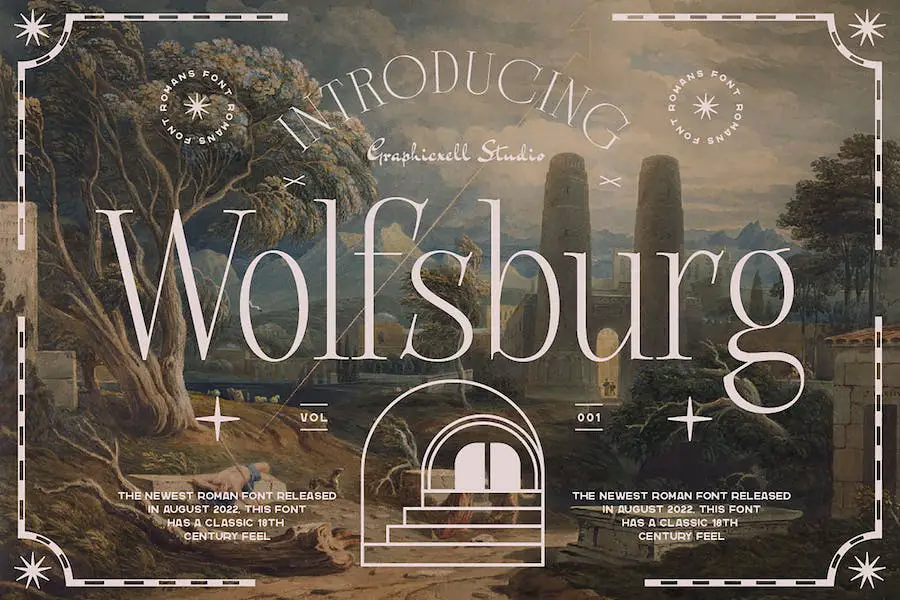
Wolfsburg adalah font Romawi yang terinspirasi dari logo minimalis. Ini sempurna untuk mendesain template, brosur, video, branding iklan, logo, undangan, desain tata letak, kerajinan elegan, dan desain cantik.
Cinta Romawi
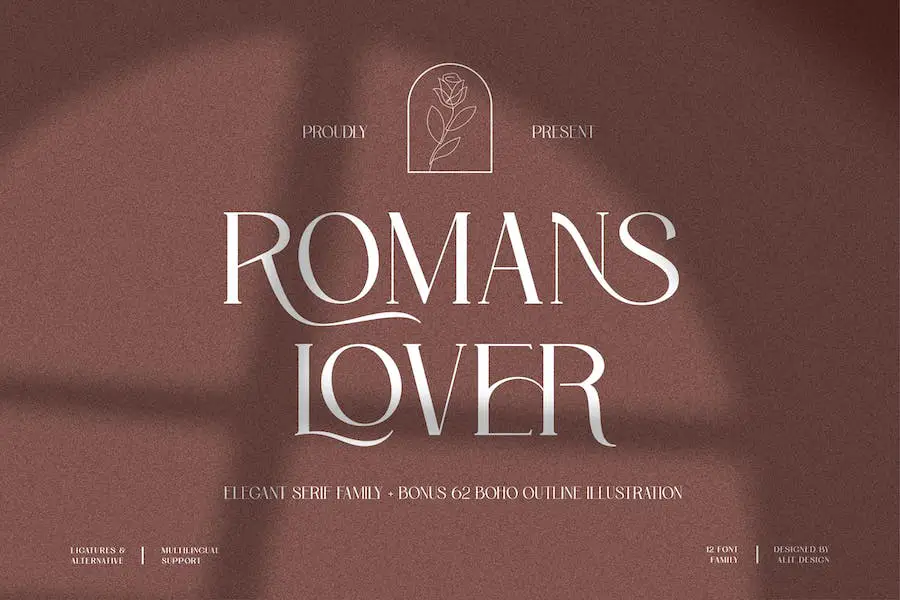
Roman Love adalah font luar biasa yang sempurna untuk desainer grafis yang ingin menyempurnakan proyek mereka. Font ini dikenal dengan gaya serif yang elegan dan dinamis, yang menambahkan sentuhan kecanggihan pada desain apa pun.
Dengan bentuk yang halus dan mengalir, Roman Love menciptakan lekukan yang unik dan indah yang pasti akan menarik perhatian.
Salah satu keuntungan terbesar Roman Love adalah keserbagunaannya. Font ini dapat dengan mudah diterapkan pada berbagai desain, terutama yang memiliki konsep elegan dan halus.
Roma
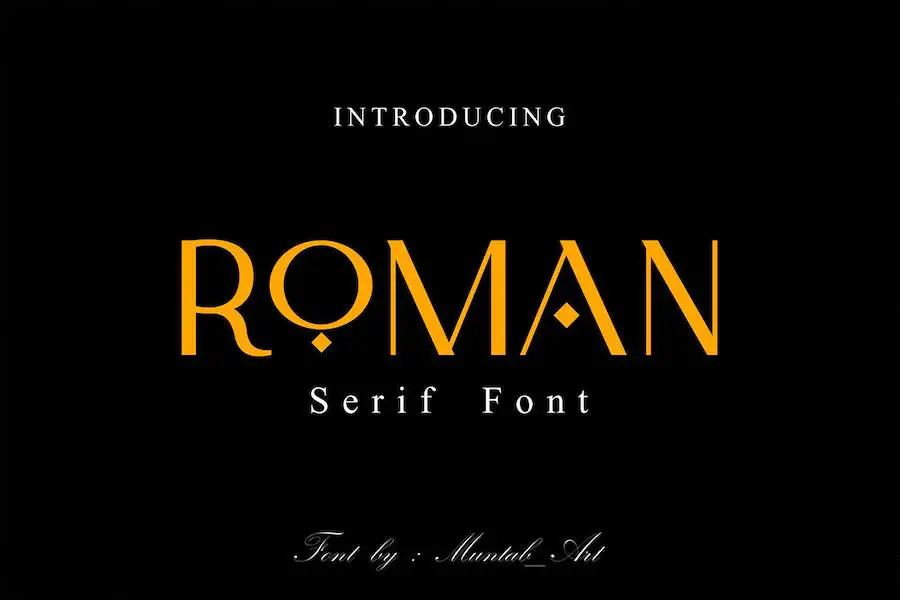
Roman Fonts adalah jenis huruf serbaguna yang menawarkan huruf besar, angka, dan berbagai macam tanda baca. Font serif ini memadukan gaya klasik dan timeless dengan sentuhan modern, sehingga cocok untuk berbagai proyek desain.
Baik Anda membuat poster, desain web, materi branding, ilustrasi, atau lencana, Roman Fonts siap membantu Anda.
Dengan tampilannya yang bersih dan elegan, Roman Fonts memberikan sentuhan kecanggihan pada desain Anda. Bentuk hurufnya yang dibuat dengan hati-hati menambah sentuhan profesionalisme, menjadikannya sempurna untuk proyek formal dan informal.
Pemancing
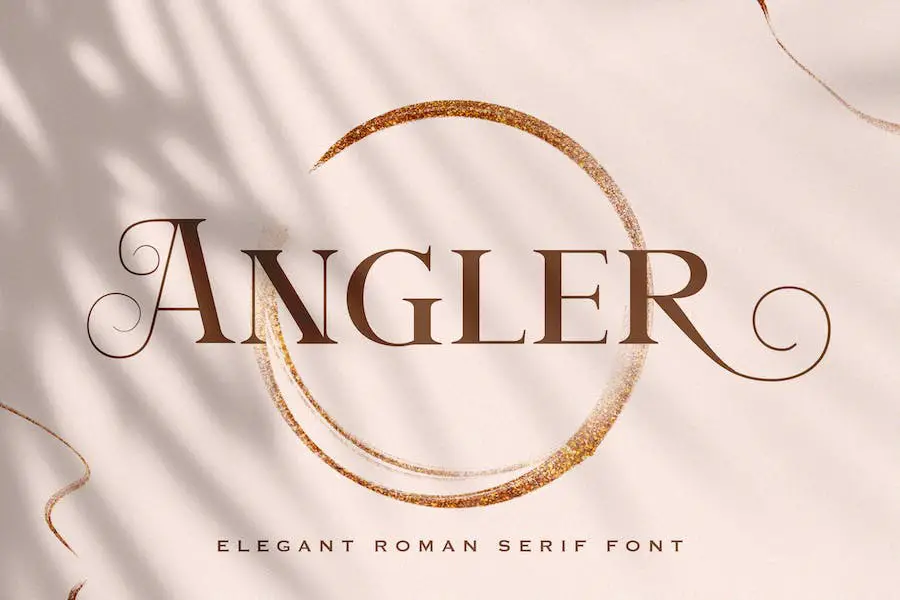
Angler adalah font Romawi fantastis yang menambahkan sentuhan keaslian dan keanggunan pada proyek apa pun. Dengan desain serif yang rapi dan klasik, ide kreatif Anda langsung menonjol dari yang lain.
Salah satu hal terbaik tentang Pemancing adalah keserbagunaannya. Ini dengan mulus cocok dengan berbagai proyek, memastikan bahwa desain Anda selalu terlihat profesional dan halus.
Baik Anda membuat logo, situs web, atau iklan cetak, Angler akan meningkatkan pekerjaan Anda ke level selanjutnya.
Waluxe
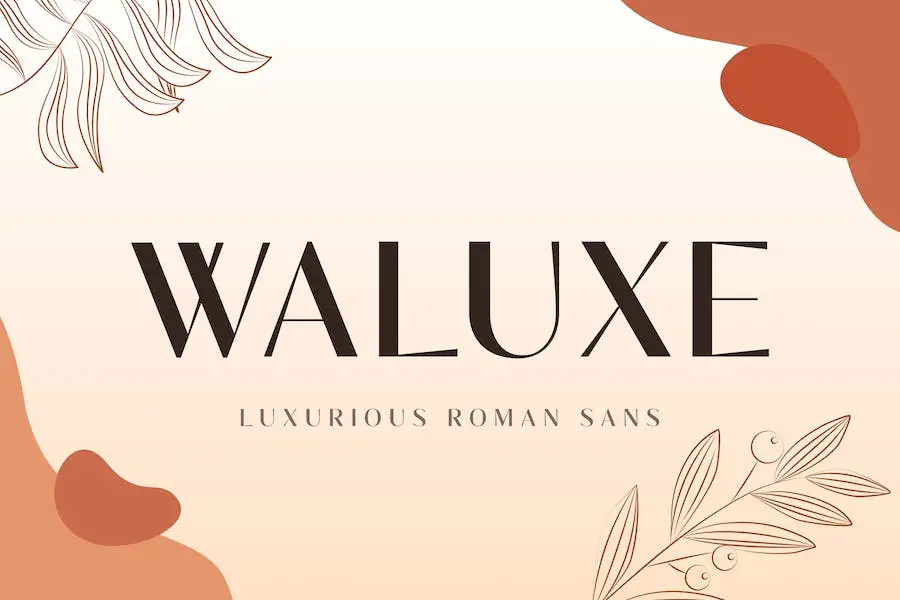
'Memperkenalkan Waluxe – font sans Romawi mewah yang mengambil inspirasi dari logo minimalis yang terkenal. Ini adalah font yang sempurna untuk mendesain brosur, template, video, branding iklan, logo, dan banyak lagi.
Dengan penginstalan sederhana, Anda dapat dengan mudah menggunakannya di Adobe Illustrator, Adobe Photoshop, Adobe InDesign, dan bahkan Microsoft Word. Font ini juga menyertakan karakter yang disandikan PUA, yang artinya dapat diakses sepenuhnya tanpa memerlukan perangkat lunak desain tambahan.
Plus, ini mendukung banyak bahasa, sehingga Anda dapat menggunakannya untuk proyek internasional. Dengan mesin terbang standar dan kompatibilitas dengan PC dan Mac, Waluxe adalah font serbaguna yang akan meningkatkan proyek desain Anda ke tingkat keanggunan yang baru.
Roma ionik
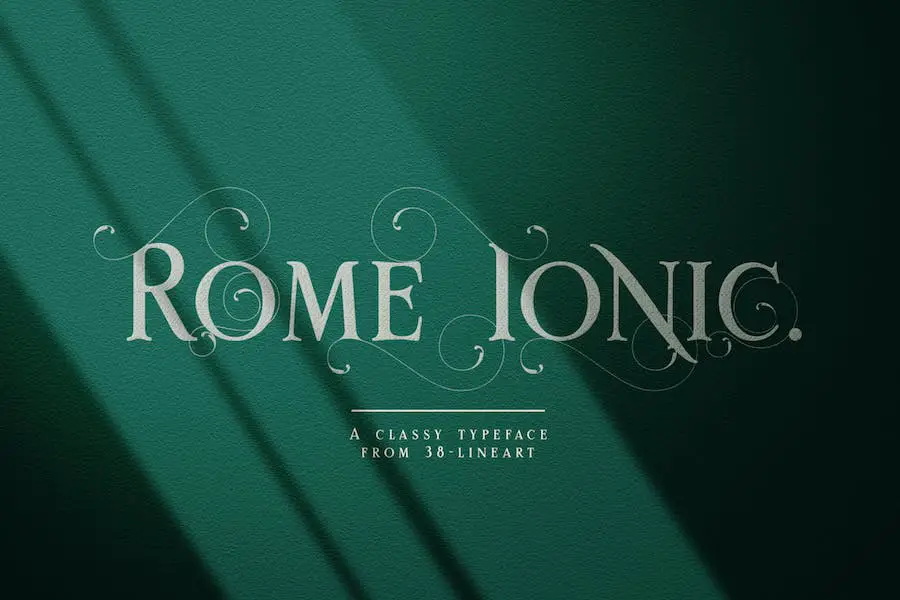
Rome Ionic adalah font tampilan serif yang menakjubkan yang menarik inspirasi dari fitur arsitektur kolom bangunan Romawi kuno. Secara khusus, ini mengambil inspirasi dari kolom ionik yang tinggi dan ramping, yang dikenal dengan desain spiral geometrisnya.
Basis font dibentuk dengan serif, memberikan tampilan yang ramping dan menjulang tinggi. Itu juga dilengkapi dengan 8-18 pergantian set gaya, memungkinkan lebih banyak kemungkinan desain.
Dengan Rome Ionic, Anda dapat meningkatkan proyek Anda ke tingkat kecanggihan dan daya tarik visual yang baru. Estetika Romawi kunonya menghadirkan sentuhan sejarah dan keagungan, menjadikannya pilihan fantastis bagi desainer grafis yang ingin menyempurnakan proyek mereka dengan font yang kuat dan tak lekang oleh waktu.
Yunani Romawi
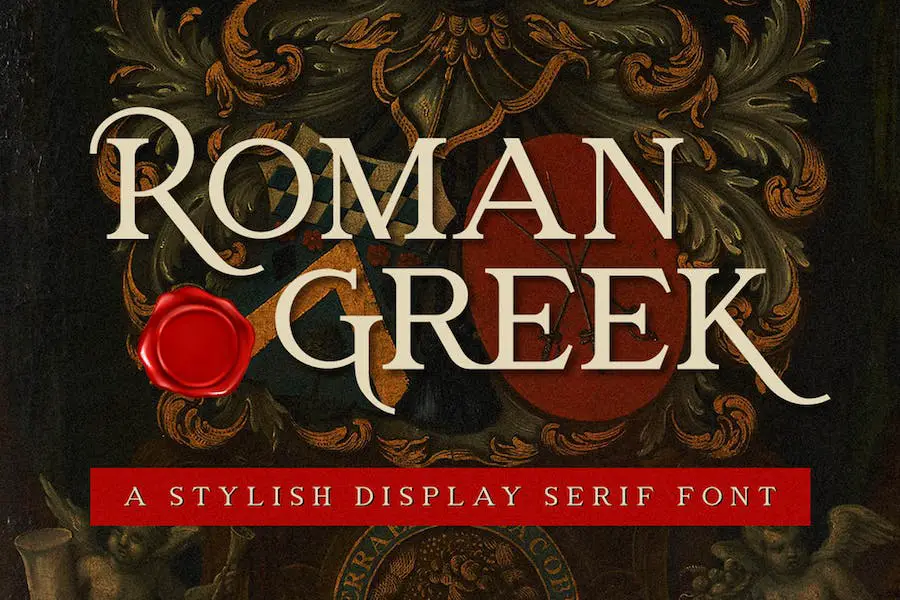
Roman Greek adalah font serif yang elegan dan berbeda yang sempurna untuk semua jenis desain. Gayanya yang rapi dan sederhana membuatnya serbaguna dan cocok untuk segala acara. Dengan berbagai macam aplikasinya, Roman Greek memiliki potensi untuk menjadi font pilihan Anda.
Ini tersedia dalam format OTF, TTF, dan WOFF, membuatnya dapat diakses di Adobe Illustrator, Adobe Photoshop, Adobe InDesign, dan bahkan Microsoft Word.
Font ini dikodekan PUA, yang artinya dapat diakses sepenuhnya tanpa memerlukan perangkat lunak desain tambahan. Dengan bahasa Yunani Romawi, Anda dapat meningkatkan tampilan proyek Anda dan menambahkan sentuhan kecanggihan.
Kebanggaan Romawi
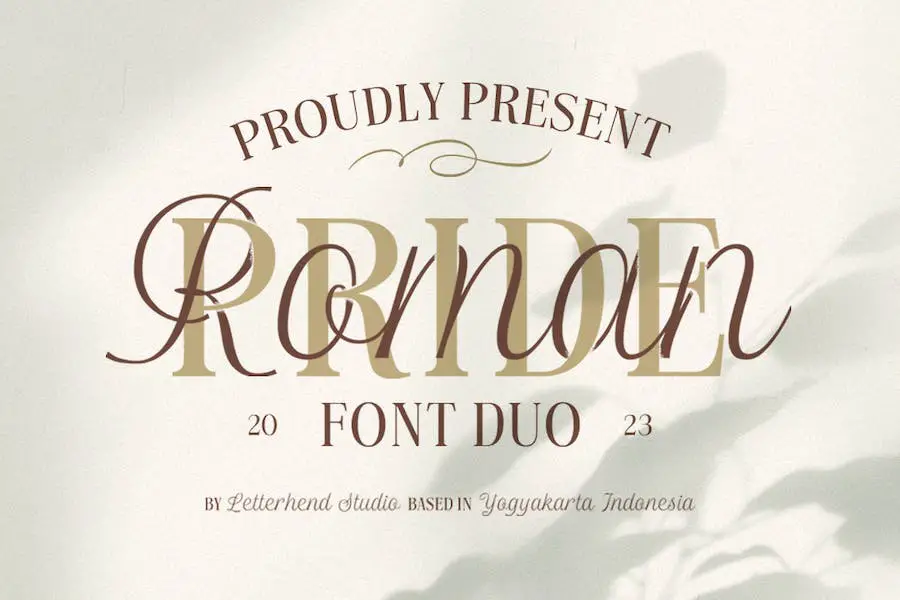
Roman Pride, duo font yang menampilkan font serif yang elegan dan font skrip yang menawan, menggabungkan gaya klasik dan modern untuk menyempurnakan desain Anda.
Ini termasuk huruf besar dan kecil, angka, tanda baca, alternatif, dan pengikat, dan mendukung banyak bahasa.
Untuk mengakses sepenuhnya semua variasi, kami sarankan untuk menggunakan program seperti Adobe Apps atau Corel Draw yang mendukung fitur OpenType dan panel Glyphs. Berikan sentuhan elegan pada proyek Anda dengan duo font Roman Pride.
Roma
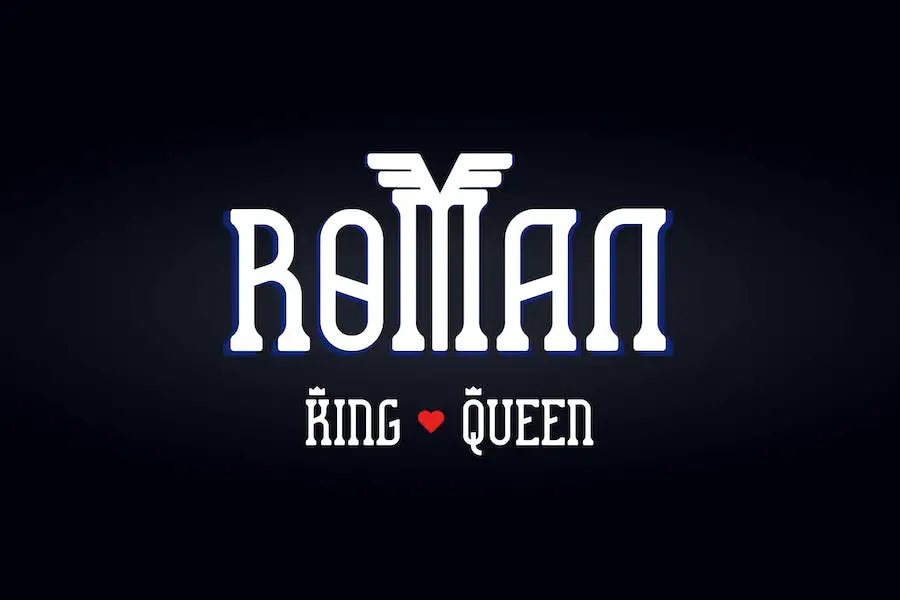
Roman adalah font tampilan yang menghadirkan sentuhan keanggunan dan keunikan pada proyek desain Anda. Apakah Anda sedang membuat poster, kartu, judul buku, atau bahkan judul artikel berita, Roman memiliki karakter khusus yang Anda cari.
Roman dirancang untuk memikat audiens Anda dan membuat desain Anda menonjol. Tampilannya yang stylish dan canggih menambahkan sentuhan berkelas pada proyek apa pun. Garis yang bersih dan jelas dari font ini memastikan bahwa pesan Anda tersampaikan dengan jelas dan berdampak.
Salah satu fitur menonjol dari Roman adalah keserbagunaannya. Ini dapat digunakan dalam berbagai aplikasi desain, termasuk spanduk, selebaran, dan alat tulis yang berbeda. Apa pun proyek Anda, Roman dapat meningkatkan desainnya dan membuatnya benar-benar berkesan.
Roma
Romans adalah duo font bernama ROMANS Rexamples yang menambahkan sentuhan keanggunan dan harmoni pada proyek desain Anda. Apakah Anda sedang mengerjakan logo, desain pernikahan, postingan media sosial, iklan, atau desain produk, duo font ini adalah pilihan yang sempurna.
Dengan gaya tipografinya yang indah, itu akan memberi proyek Anda tampilan yang profesional dan canggih.
Font menawarkan berbagai pilihan, memungkinkan Anda untuk menyesuaikan dan bereksperimen dengan gaya yang berbeda sesuai dengan kebutuhan Anda. Ini adalah pilihan serbaguna yang akan meningkatkan daya tarik visual proyek apa pun.
Romawi Hitam
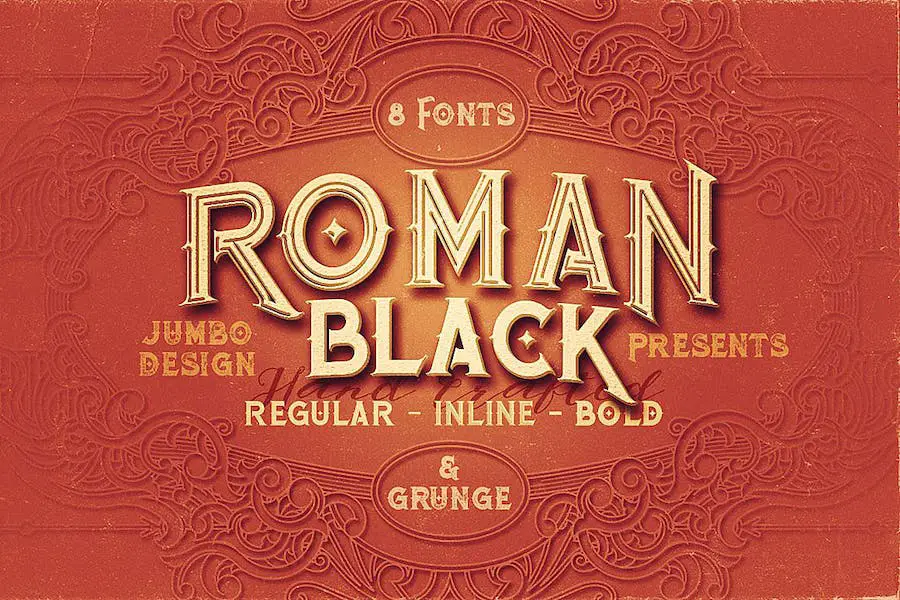
Roman Black adalah font serif kustom satu-satunya yang memancarkan gaya vintage dan ornamental.
Dengan 8 gaya berbeda untuk dipilih, termasuk regular, grunge, inline grunge, bold, bold grunge, bold inline, dan bold inline grunge, font ini menawarkan keserbagunaan dan kreativitas untuk semua proyek desain Anda.
Untuk memastikan jarak yang optimal dan daya tarik visual, cukup sesuaikan pengaturan kerning ke 'optical' di jendela karakter Photoshop.
Romawi Picisan
Roman Picisan adalah font sans serif yang canggih dan menawan yang menambahkan sentuhan modis pada proyek apa pun. Didesain khusus untuk desain mewah, elegan, dan feminin, font ini sangat cocok untuk menciptakan desain modern dan apik.
Dengan format OTF dan file alternatifnya, termasuk opsi huruf besar dan kecil, ini menyediakan berbagai kemungkinan kreatif.
Apakah Anda sedang mengerjakan proyek branding, desain situs web, atau proyek desain grafis lainnya, Roman Picisan adalah pilihan yang dapat diandalkan. Keindahan dan fungsinya membuatnya cocok untuk berbagai industri, termasuk fashion, kecantikan, dan gaya hidup.
mode mawar
Rosemode adalah font serif elegan yang sempurna untuk berbagai proyek. Dengan desainnya yang mewah, sangat ideal untuk membuat logo dan branding kelas atas. Ini juga bekerja dengan baik untuk desain editorial berkelas, majalah wanita, dan merek kosmetik.
Apakah Anda perlu merancang promosi mode, branding galeri seni, pameran museum, atau karya arsitektur bersejarah, Rosemode siap membantu Anda.
Ini juga bagus untuk branding butik, desain alat tulis, desain blog, periklanan modern, undangan kartu, kutipan seni, dekorasi rumah, judul buku dan sampul, serta acara khusus. Kemungkinannya tidak terbatas dengan Rosemode!
Roman Langston
Roman Langston adalah font tanda tangan modern memukau yang memancarkan kelas, keanggunan, dan sentuhan kontemporer. Dengan desainnya yang cantik dan serbaguna, font ini sangat ideal untuk berbagai proyek desain grafis.
Apakah Anda sedang mengerjakan tanda tangan, alat tulis, logo, undangan pernikahan, kutipan tipografi, sampul majalah, atau tajuk situs web, Roman Langston akan meningkatkan desain Anda ke ketinggian baru.
Font ini tidak hanya cocok untuk proyek tradisional tetapi juga menambahkan sentuhan modis dan editorial untuk branding dan desain yang berhubungan dengan fashion.
Kisah Roma
Romans Story adalah font ligatur serif canggih yang memancarkan kesan mewah dan kualitas premium. Dibuat dengan hati-hati dengan perhatian terhadap detail, jenis huruf ini menonjol dari font serif biasa dengan ligaturnya yang unik.
Sangat cocok untuk menambahkan sentuhan elegan pada logo, headline, judul, dan berbagai bentuk formal seperti undangan, label, jenis majalah, buku, kartu ucapan, kemasan, fashion, makeup, alat tulis, novel, dan iklan.
Dengan keserbagunaannya, font ini harus dimiliki oleh desainer grafis yang ingin meningkatkan proyek mereka dengan sentuhan kecanggihan.
Romawi Canggih
Memperkenalkan Roman Sophisticated, jenis huruf mewah dan modern yang akan meningkatkan proyek desain Anda ke tingkat keanggunan dan kecanggihan yang baru.
Font ini sangat cocok untuk heading, logo, branding, majalah, kemasan produk, dan undangan. Dengan garis yang bersih dan lekukan yang halus, Roman Canggih menambahkan sentuhan berkelas pada proyek apa pun.
Hal pertama yang akan Anda perhatikan tentang Roman Canggih adalah tampilannya yang ramping dan bergaya. Garis-garis yang bersih dan lekukan yang halus memberi font ini tampilan yang canggih dan modern yang pasti akan menarik perhatian.
Font Romawi Gratis Terbaik
Ingin menambahkan sentuhan keanggunan klasik pada proyek desain Anda? Tidak terlihat lagi dari font Romawi gratis yang fantastis ini! Lihat dan ubah desain Anda dengan keindahan abadi.
SD Roma
Roman SD adalah font serbaguna yang sempurna untuk desainer grafis yang ingin meningkatkan desain proyek mereka. Ini adalah font gratis 100% yang dibuat oleh Steve Deffeyes, menyediakan sumber daya yang luar biasa untuk desainer tanpa biaya apa pun.
Dengan desainnya yang ramping dan elegan, Roman SD menambahkan sentuhan kecanggihan pada proyek apa pun. Ini menawarkan berbagai atribut, termasuk estetika yang bersih dan abadi, keterbacaan yang sangat baik, dan jenis huruf Romawi klasik.
Dengan Roman SD, desainer dapat dengan mudah menyempurnakan desain mereka dan memikat audiens mereka.
Agustus
Augustus adalah font yang menghadirkan sentuhan keanggunan dan kecanggihan pada setiap proyek desain grafis. Dengan desainnya yang ramping dan tak lekang oleh waktu, ia memikat perhatian pemirsa dan meningkatkan daya tarik estetika secara keseluruhan.
Kurvanya yang anggun dan jarak yang sangat seimbang membuatnya ideal untuk membuat logo yang menakjubkan, bahan branding, dan tipografi yang menarik. Apakah Anda sedang mengerjakan desain situs web, brosur, atau pengemasan, Augustus pasti akan meningkatkan pekerjaan Anda ke tingkat yang lebih tinggi.
Keserbagunaannya memungkinkan untuk digunakan dalam berbagai proyek, menjadikannya font yang harus dimiliki oleh setiap desainer grafis yang ingin menambahkan sentuhan kelas pada pekerjaan mereka.
Serat
Serat adalah font serbaguna yang memadukan elemen tipografi klasik dengan keanggunan tulisan tangan Latin awal.
Font serif dengan kontras sedang ini menawarkan versi modern dari huruf kecil Carolingian untuk huruf kecil, dengan batang vertikal dimodifikasi untuk memiliki potongan horizontal untuk tampilan kaligrafi yang disederhanakan.
Huruf besar adalah serif menyala yang terinspirasi oleh huruf kapital Romawi, menambahkan sentuhan kecanggihan pada desain apa pun.
Morin Muda
Young Morin adalah font yang sempurna untuk penggunaan pribadi tetapi tidak cocok untuk penggunaan komersial. Penting untuk diperhatikan bahwa ini hanyalah demo dan tidak boleh digunakan untuk proyek komersial apa pun.
Namun, jika Anda mencari font untuk menambahkan sentuhan unik pada proyek pribadi Anda, Young Morin adalah pilihan yang tepat. Itu dibuat oleh Alit Design dan tersedia secara gratis, meskipun sumbangan sangat dihargai.
Font itu sendiri memiliki nuansa modern dan gaya, membuatnya ideal untuk desainer grafis yang ingin menyempurnakan desain proyek mereka.
Pac Liberta
Pac Libertas adalah font gratis 100% yang dibuat oleh Evaldas Klupsas. Font Romawi ini sangat cocok untuk desainer grafis yang ingin menyempurnakan desain proyek mereka. Dengan gayanya yang bersih dan elegan, Pac Libertas menambahkan sentuhan kecanggihan pada desain apa pun.
Atribut Pac Libertas menjadikannya pilihan yang bagus untuk desainer grafis. Bentuk huruf Romawi klasiknya menghadirkan pesona abadi pada desain Anda, sementara keterbacaannya memastikan bahwa pesan Anda mudah dipahami.
Keserbagunaan font memungkinkannya digunakan dalam berbagai proyek, mulai dari logo dan iklan hingga situs web dan grafik media sosial.
Pertanyaan yang Sering Diajukan
Font Romawi mengacu pada gaya tipografi tertentu yang berasal dari Roma kuno. Font-font ini dicirikan oleh desainnya yang bersih dan sederhana, dengan serif lurus dan sapuan berbobot rata. Mereka sering digunakan untuk memberikan tampilan klasik dan elegan pada teks.
Untuk menggunakan font Romawi secara efektif, penting untuk mempertimbangkan konteks dan tujuan desain Anda. Font Romawi bekerja dengan baik untuk pengaturan formal dan tradisional, seperti undangan pernikahan, sertifikat, atau makalah akademis.
Namun, mereka mungkin tidak cocok untuk proyek yang lebih modern atau kreatif. Pastikan untuk memasangkannya dengan font pelengkap dan sesuaikan ukuran dan spasi untuk keterbacaan yang optimal.
Ya, font Romawi dapat digunakan untuk konten digital. Banyak situs web dan aplikasi menggabungkan font Romawi untuk mempertahankan estetika yang canggih dan tak lekang oleh waktu.
Namun, sangat penting untuk memastikan bahwa font Roman yang dipilih aman untuk web dan kompatibel di berbagai perangkat dan browser untuk menghindari potensi masalah tampilan.
Kesimpulan
Sebagai kesimpulan, kami telah menjelajahi dunia font Romawi dan bagaimana mereka dapat menyempurnakan desain proyek Anda. Kami membahas sejarah font Romawi, karakteristiknya, dan tip tentang cara memilih font yang tepat untuk desain Anda.
Dengan memanfaatkan font Romawi, Anda dapat menghadirkan kesan elegan, canggih, dan keindahan abadi pada proyek Anda.